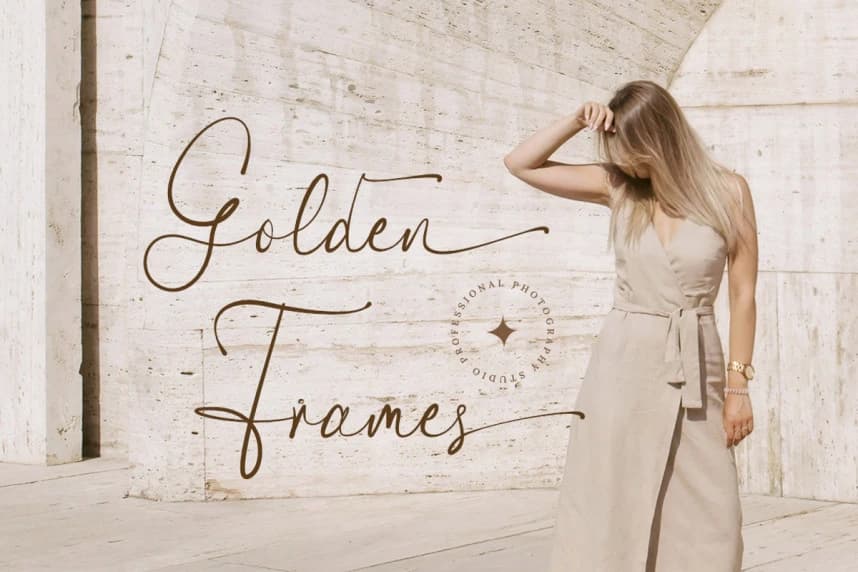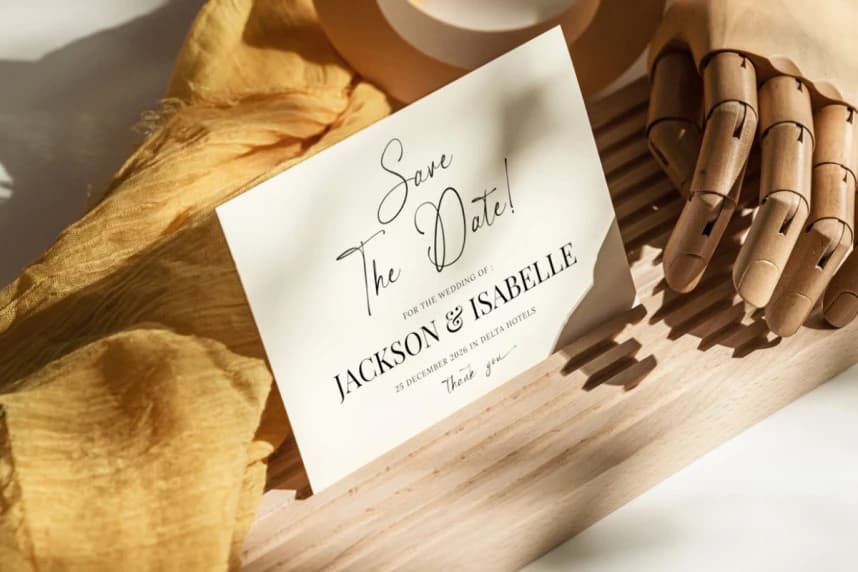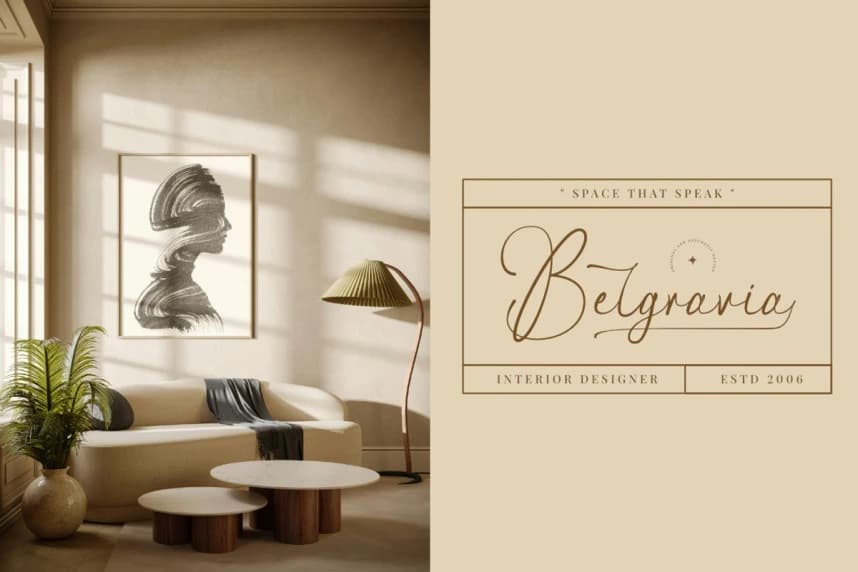
Majestica Royale Font
Majestica Royale Font, lüks ve profesyonel bir görünüm için tasarlanmış premium bir script fontudur. Geleneksel kaligrafinin güzelliğini temiz, modern bir dokunuşla birleştirir. Eğer pahalı görünen, zarif ve okunması kolay bir font arıyorsanız, bu mükemmel tercihtir.
Majestica Royale Font, lüks ve profesyonel bir görünüm için tasarlanmış premium bir el yazısı fontudur. Geleneksel kaligrafinin güzelliğini temiz, modern bir dokunuşla birleştirir. Eğer pahalı görünen, zarif ve okunması kolay bir yazı tipi arıyorsanız, bu mükemmel bir tercihtir.
Majestica Royale